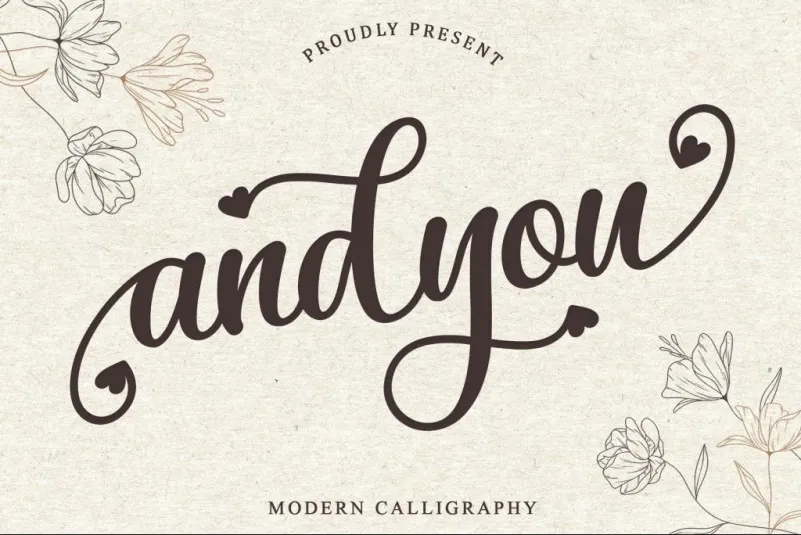
Andyou Font – Download Grátis
Esta é uma das fuentes modernas inspiradas na calligrafia que vem com um estilo encantador, conectando no meio do coração. Foi projetada com alta detalhe para apresentar um estilo luxuoso e sofisticado. Esta font foi meticulosamente criada para aqueles que buscam um olhar agradável e renovador em suas criações. Andyou é PUA (Propriedade de Uso Ampliado) codificada, o que significa que você pode acessar facilmente todos os caracteres e swashes sem qualquer dificuldade. A fonte é ideal para quem procura uma opção moderna para adicionar um toque autêntico em seus designs digitais.